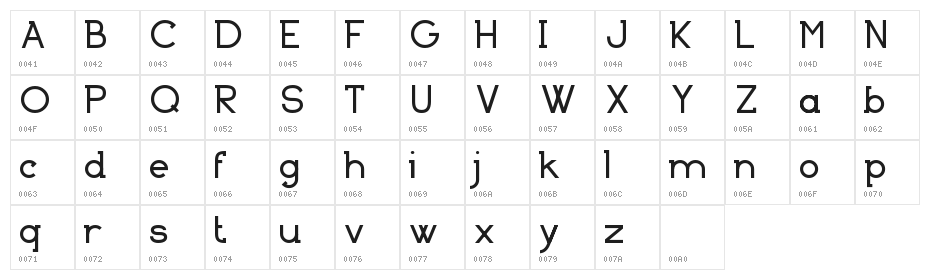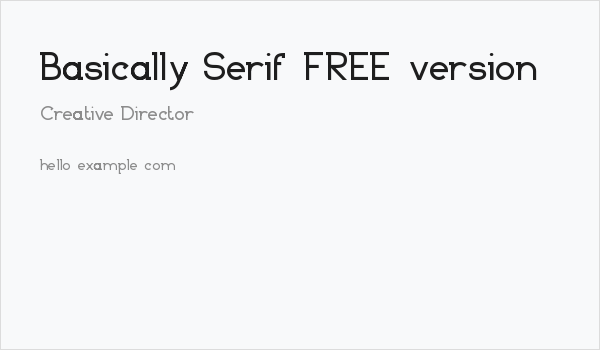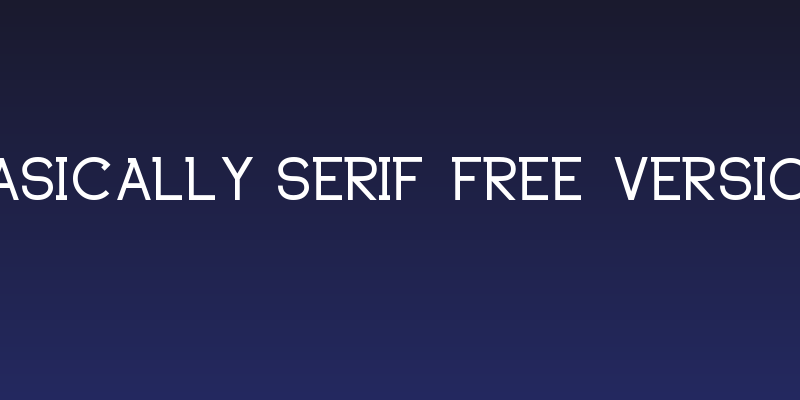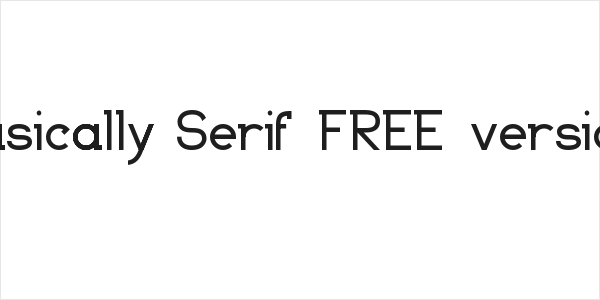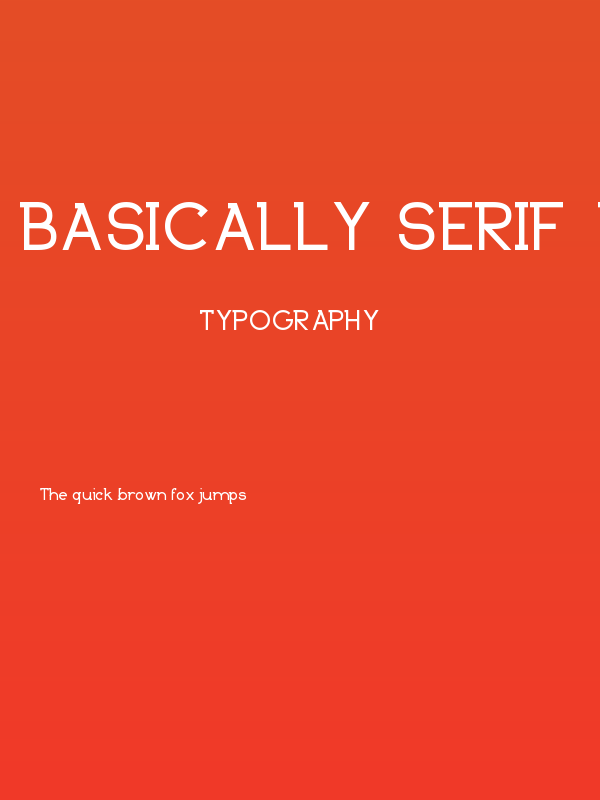
Basically Serif_FREE-version Font
✎ Serif
| Projets proposés | Ideal for editorial design, branding projects, and digital content where a modern yet classic look is desired. |